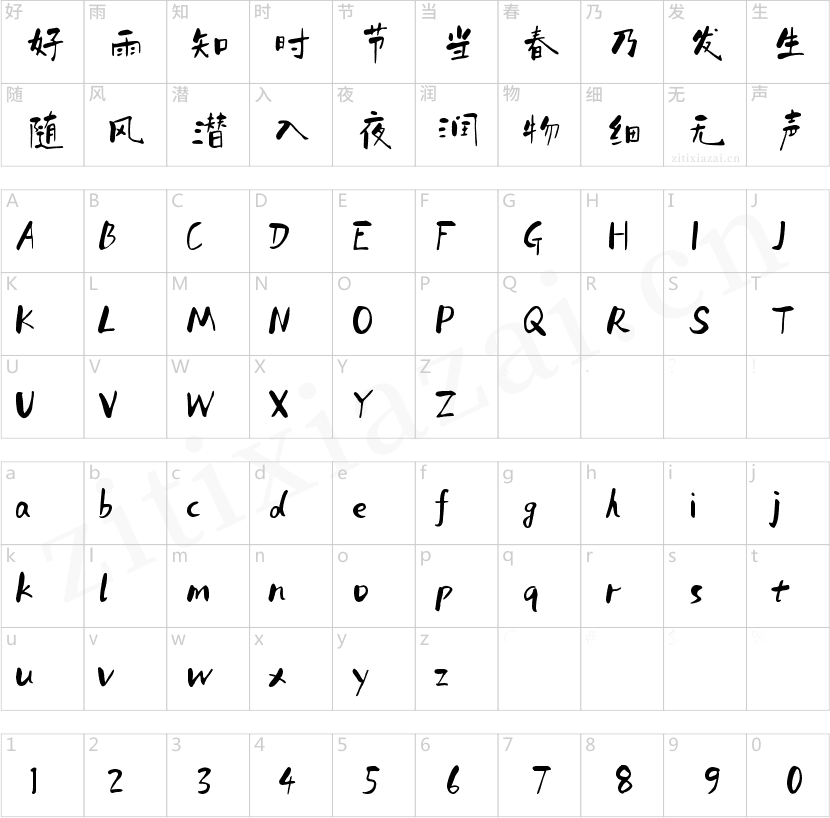
Aa人间蹉跎
Aa人间蹉跎字体
Aa人间蹉跎是一款非常具有艺术性的字体,它的设计灵感来源于对古典艺术的研究,同时又融入了现代字体设计的元素。字形优美,笔画粗细变化自然,给人以大气、典雅的感觉。Aa人间蹉跎是一款既传统又现代的字体,它的设计充满艺术感,美观大方,实用性也非常强。无论是对于设计师还是对于普通读者来说,都是一种非常不错的字体选择。Aa人间蹉跎适合用于具有艺术感的场合,比如海报、宣传单张、书籍封面等。由于其字形流畅且具有动态感,也适合用于大量的文本排版,如报纸、杂志等。
- 字体名称:Aa人间蹉跎
- 字体全名:Aa人间蹉跎